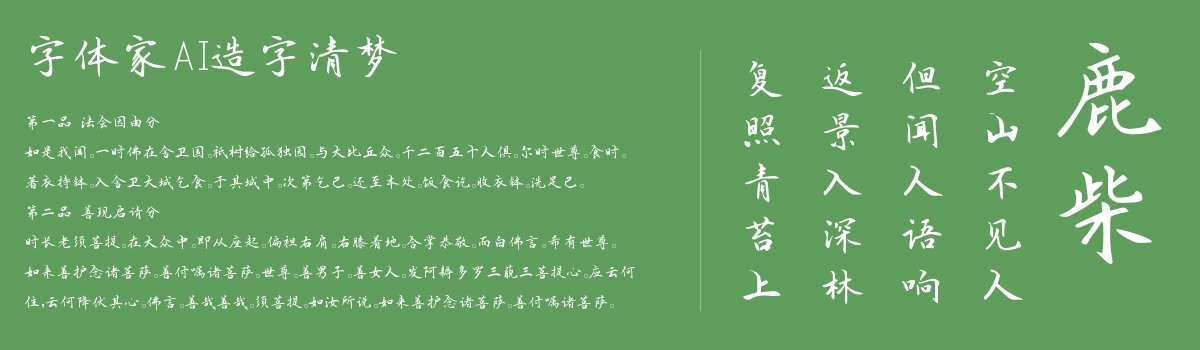
字体家AI造字清梦
字体家AI造字清梦是一款由字体家AI神笔造字生成的艺术字体,这款字体似毛笔轻蘸墨色自然书写而成,笔画有细腻的粗细变化,起笔收笔圆润柔和,无生硬棱角。横画略呈左低右高的自然倾斜,竖画挺拔却不僵直,撇捺舒展如羽翼轻展,勾画短促圆润似露珠轻坠。整体结构疏朗不拥挤,笔画间有若有若无的连丝,像水流般连贯流畅。触感如抚摸细腻宣纸,线条温润不刺手,韵律感似微风拂过柳枝,轻柔中带着自然的动态美,兼具手写的灵动与书法的雅致。适合用于一些广告标题、平面文案、海报标题、网页广告用字的编辑。